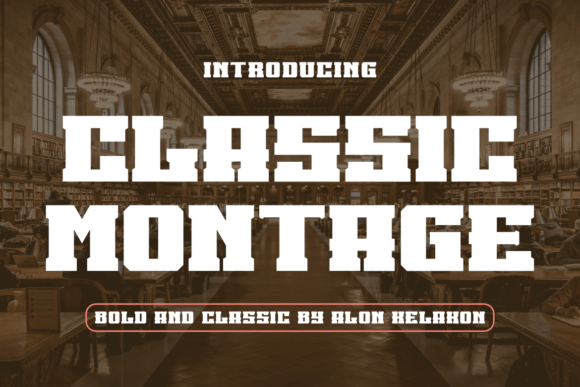
Classic Montage
Classic Montage : la police qui donne du caractère à vos projets
Vous recherchez une typographie à la fois audacieuse et polyvalente ? Classic Montage répond à toutes vos attentes. Conçue pour se démarquer, cette police unique apporte une touche rétro‑cinématographique qui s’adapte parfaitement à tous les supports : étiquettes, vêtements, affiches, titres de films, pochettes d’albums, logos, et bien plus encore.
Pourquoi choisir Classic Montage ?
- Design original – Des lettres au style vintage et dynamique qui captent immédiatement le regard.
- Polyvalence totale – Idéale pour le graphisme commercial, le branding, la mode et les projets multimédias.
- Haute lisibilité – Même à petite taille, les caractères restent nets, ce qui garantit une lecture claire sur tous les supports.
- Gain de temps – Prête à l’emploi, vous n’avez plus besoin de chercher plusieurs polices pour chaque projet.
Applications concrètes de Classic Montage
- Création d’étiquettes de produits haut de gamme.
- Design de t‑shirts, casquettes et accessoires de mode.
- Affiches de concerts, festivals et événements culturels.
- Pochettes d’albums et visuels promotionnels pour les artistes.
- Logos d’entreprise au style rétro‑moderne.
- Titres de films, bande‑annonces et génériques.
Conclusion